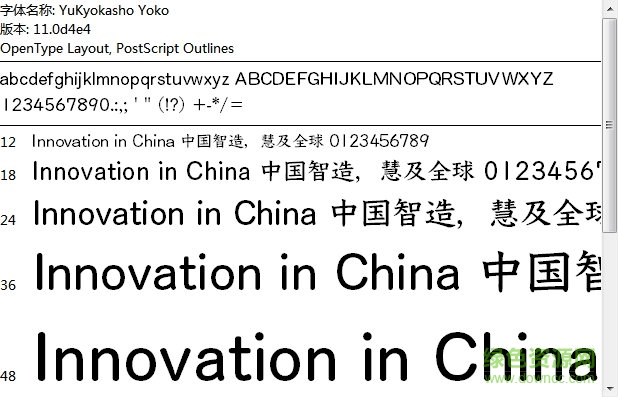
游教科書體是一款日本教科書體,字庫文正,支持日文輸入,中文漢字有著楷書字體的風(fēng)格特色,英文秀氣嚴(yán)明,非常適合排版書寫,閱讀效果不錯,需要的朋友就來綠色資源網(wǎng)試試吧!
游教科書體出自字游工房,是一家專為制作設(shè)計和風(fēng)日文字體的公司,線條粗細(xì)使用,文字結(jié)構(gòu)大方得體,給你的平面設(shè)計帶來極其精簡的體驗。
游教科書體出自NM字體家族,是一款極其出色的楷書字體,英文名稱為:Kyokasho Yoko Bold,日文名稱為:ボールド。